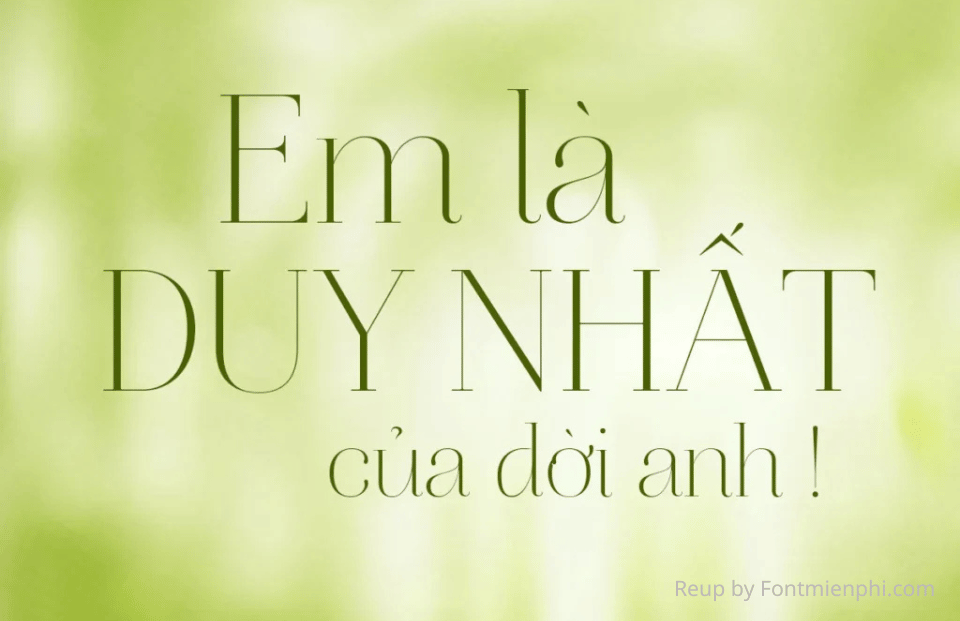
Font VL Aire Roman Pro Việt Hóa Tuyệt Đẹp Tại Font Miễn Phí
Font Miễn Phí xin giới thiệu đến bạn VL Aire Roman Pro – một bản font Việt hóa dạng có chân (serif) mang đậm chất nghệ thuật. Với đặc trưng nét chữ siêu thanh mảnh, đây là lựa chọn hoàn hảo để chèn các câu trích dẫn (quote) ý nghĩa lên ảnh, dù không thực sự tối ưu cho mục đích in ấn.
Đánh Giá Ưu & Nhược Điểm Font VL Aire Roman Pro Việt Hóa Tuyệt Đẹp
• Ưu điểm: Đường nét bay bổng, thiết kế ấn tượng. Cực kỳ phù hợp để làm Typography, banner số, hoặc chèn chữ nghệ thuật trên hình ảnh.
• Nhược điểm: Do nét chữ rất mảnh nên dễ bị mờ hoặc đứt nét khi đem đi in ấn thực tế.